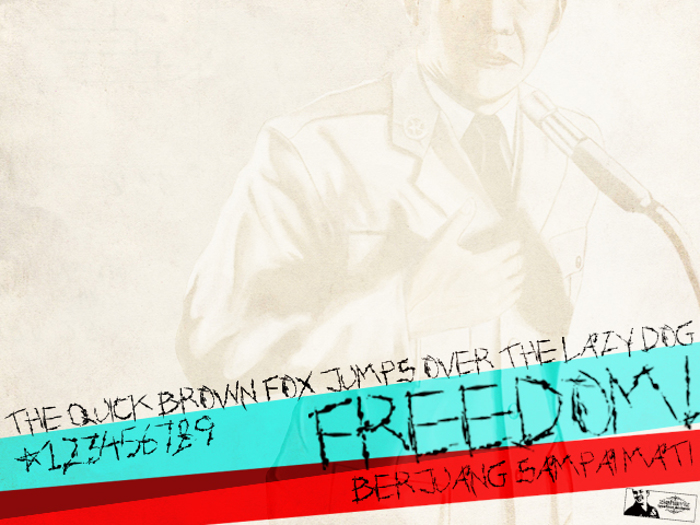
FTF Toelisan Pedjoeang Font
More info from Fizzetica TypeFoundry Indonesia
Terinspirasi dari semangat membara para pejuang dan pahlawan Bangsa Indonesia dan Hari Kemerdekaan Bangsa Indonesia 17 Agustus 1945! MERDEKA atau MATI!